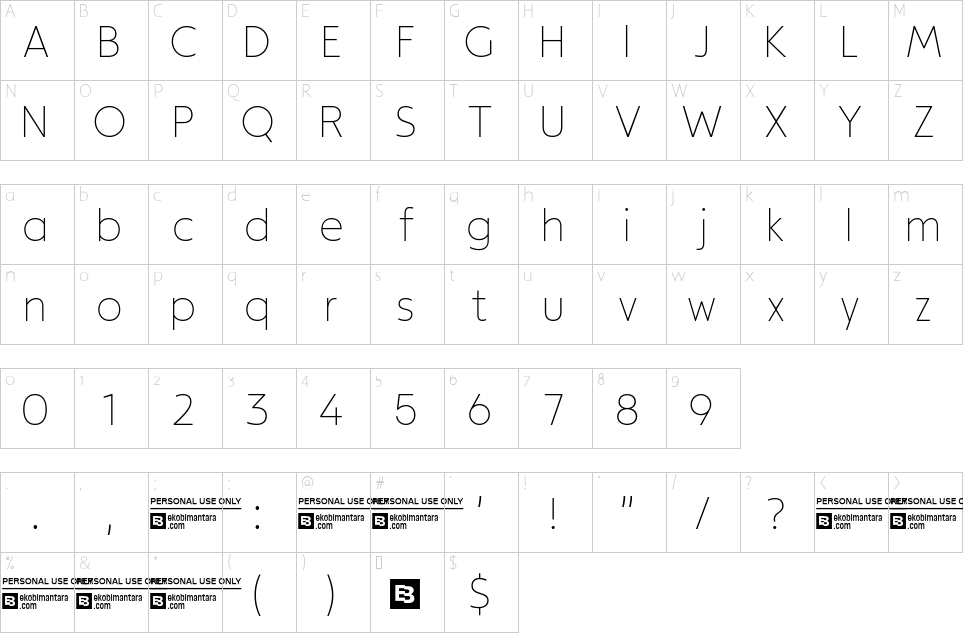
A fonte ‘Modeska Font | 1001 Free Fonts’ é uma escolha inteligente para aqueles que procuram um estilo elegante e moderno. Desenhada por Eko Bimantara, esta fonte oferece uma ampla gama de usos, desde o design de gráficos até a escrita de textos para a web. A ‘Modeska Font’ foi projetada para fornecer uma escrita agradável e profissional, com um design arredondado e leve que torna ela perfeita para o uso em sites, aplicativos e até mesmo em designs gráficos. Recentemente, esta fonte foi baixada mais de 157 vezes, demonstrando sua popularidade entre os criadores de design. Com sua interface simples e versátil, ‘Modeska Font’ é uma opção de fonte gratuita que certamente não decepcionará, permitindo-lhe expressar sua criatividade sem qualquer custo.